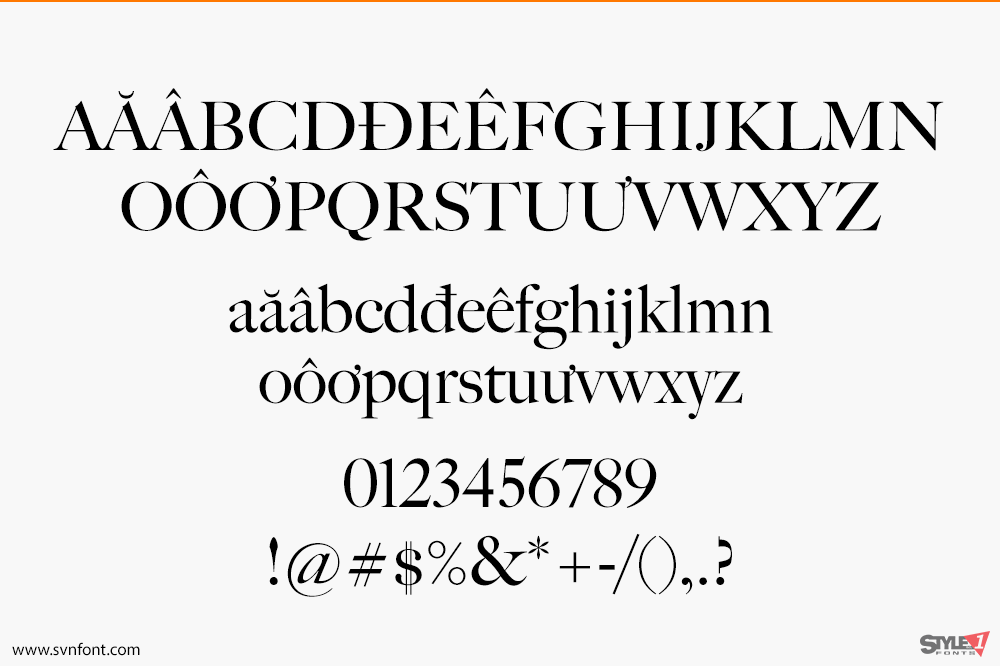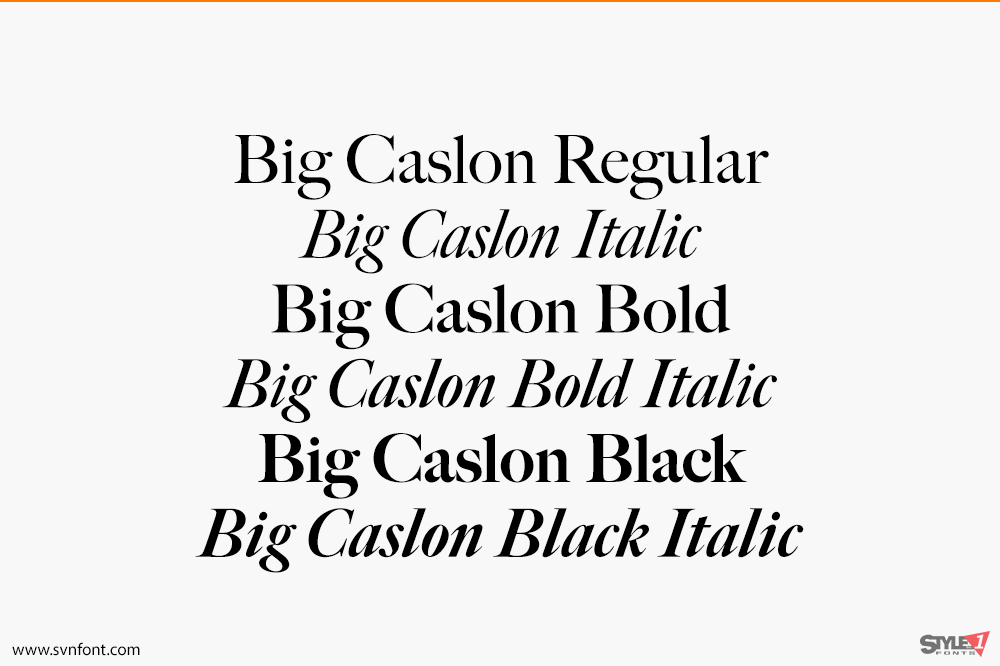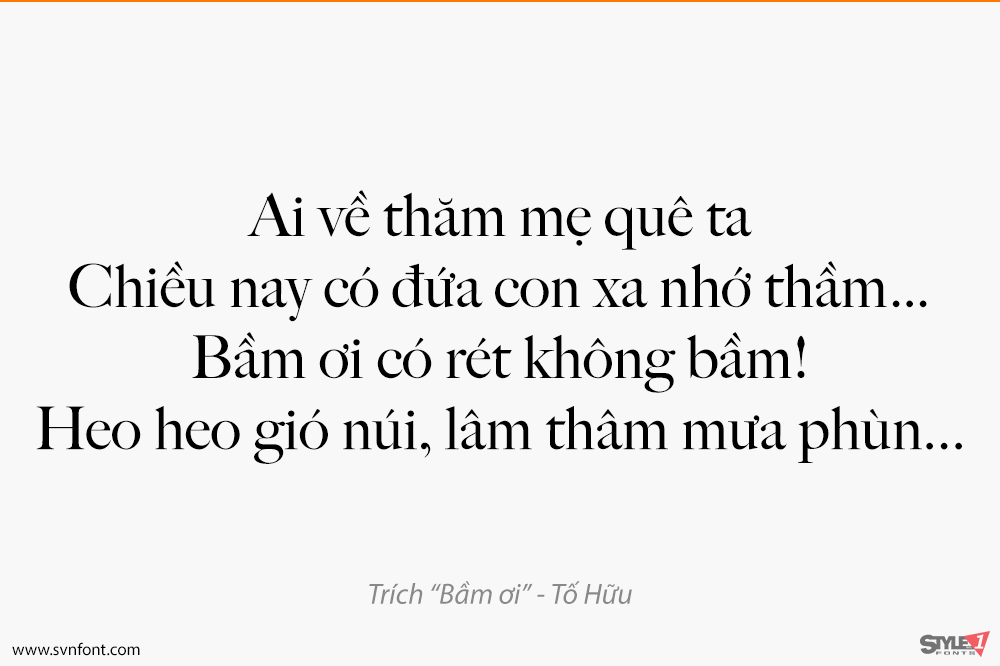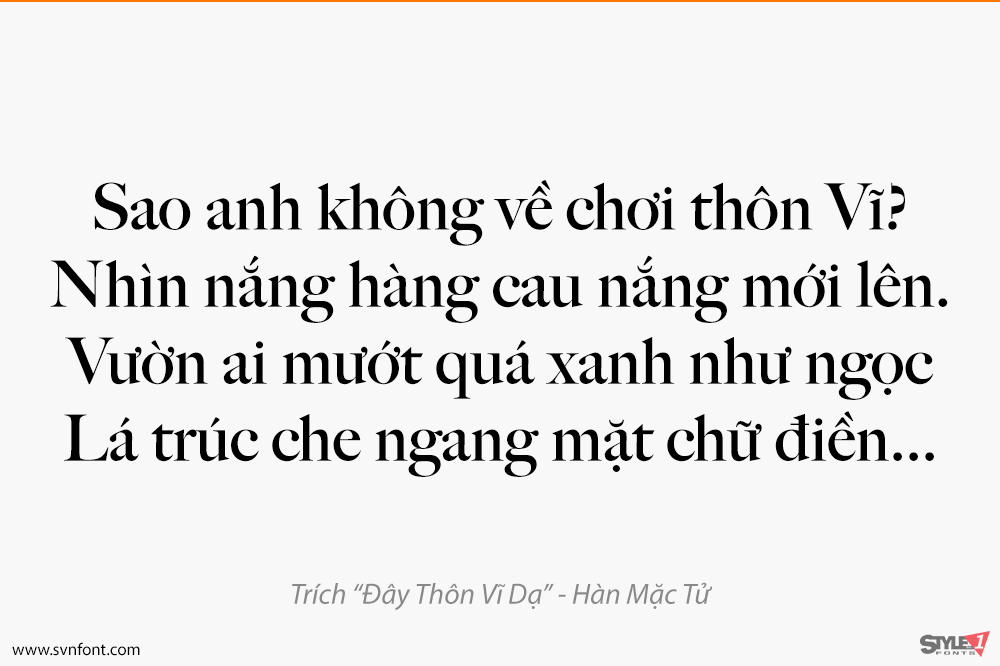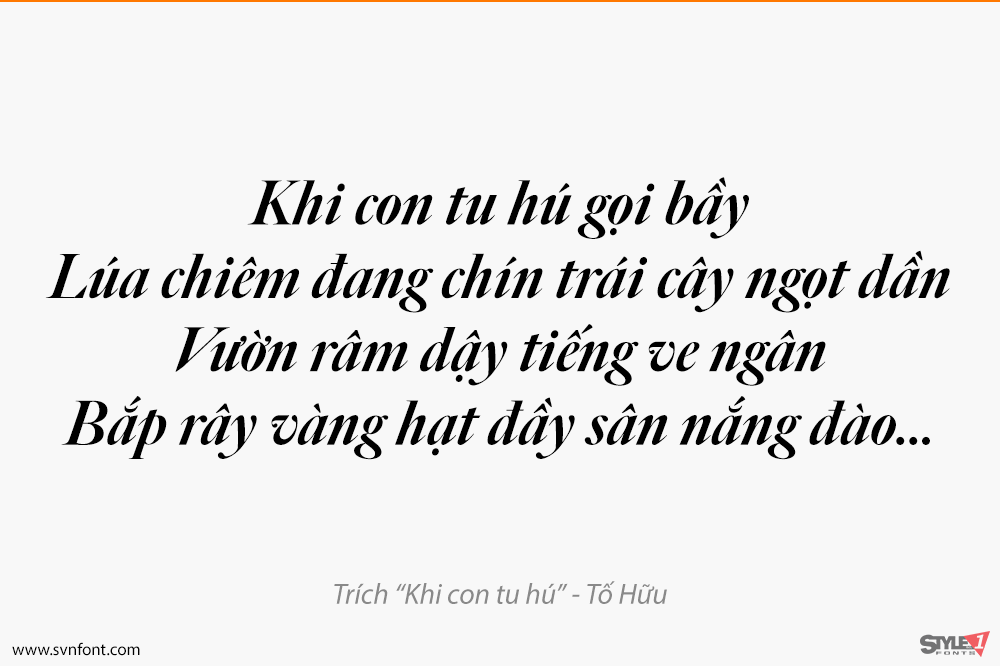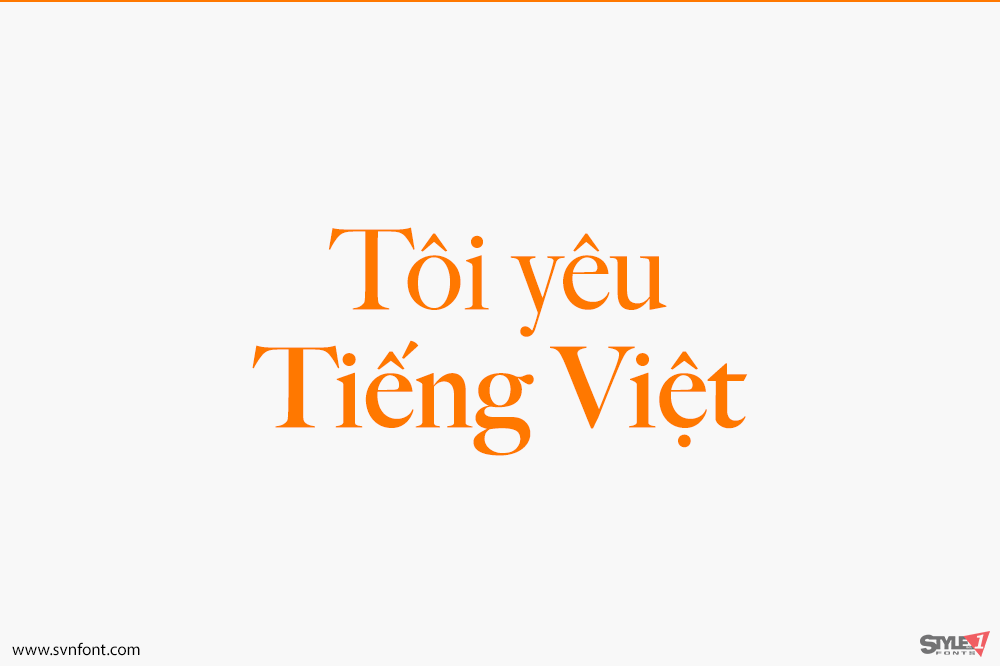
FB Big Caslon bổ sung sáu kiểu mới vào phông chữ quen thuộc và được yêu thích của Matthew Carter. Vào năm 1994, Big Caslon được phát hành dưới dạng một kiểu duy nhất, với các phông chữ riêng biệt cho chữ in hoa nhỏ, các ký tự chuyên biệt và thay thế. Giờ đây, nó là một bộ OpenType đầy đủ tính năng, đồng thời có sẵn dưới dạng webfont, với ba độ đậm (Regular, Bold, và Black). Mỗi độ đậm đều có chữ nghiêng, chữ in hoa nhỏ và nhiều ký tự thay thế nổi bật.
Nhà thiết kế: Matthew Carter
Nhà phát hành: Font Bureau; Carter & Cone